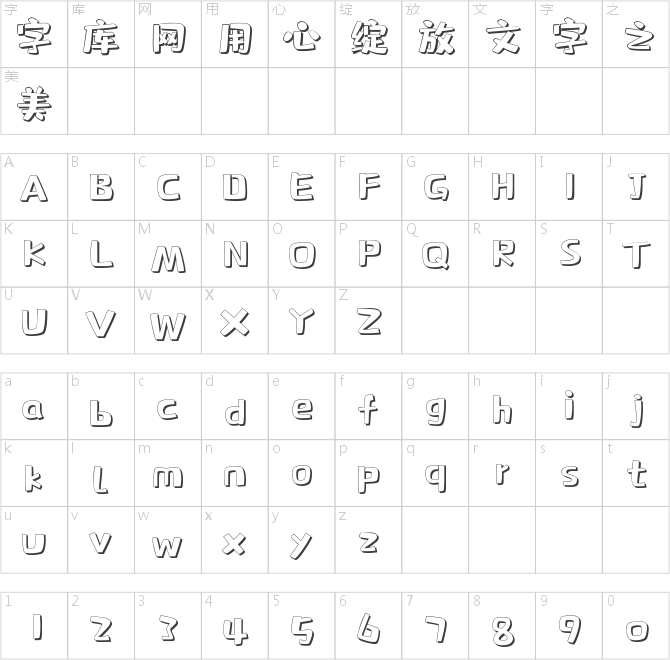
字魂39號-肥宅快樂體
該版本為空心效果字體,字符字數含6765字(包含英文、數字符號及中文簡體),適用于電商標題字體的應用。
字魂39號-肥宅快樂體字體字庫是一款讓人賞心悅目、百看不厭的中文字體,適合各類廣告和產品包裝設計應用,字體大小7.79MB,格式為ttf字體,上傳用戶是82年的拉菲,作者/版權方為字魂